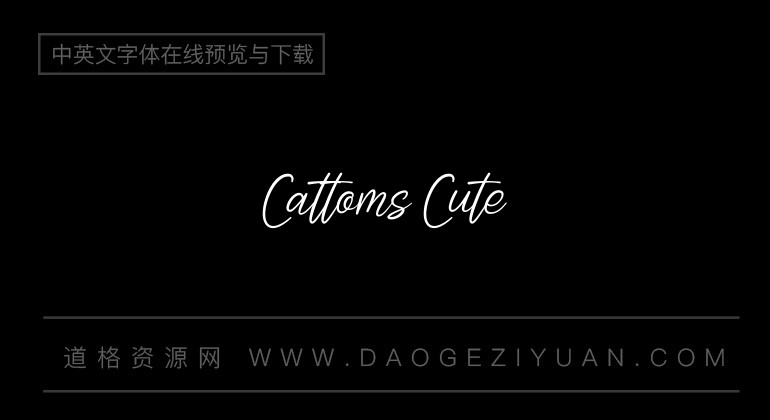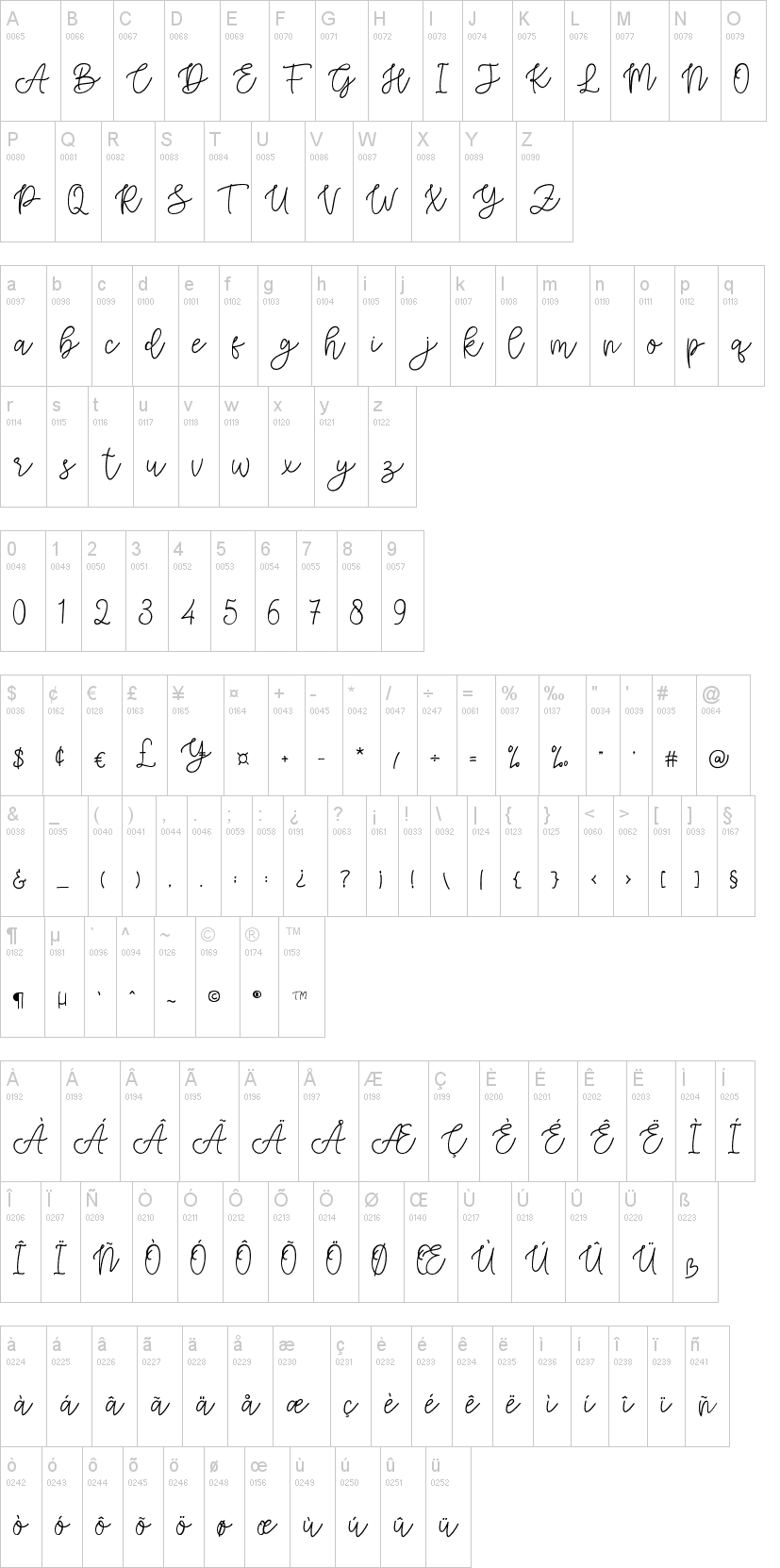
Cattoms Cute
Cattoms Cute 是一款卡通类的字体,它有着活泼可爱的样式,并且拥有大量的可爱的符号,可以用于排版,设计等等。Cattoms Cute 字体有着清晰的曲线和流畅的线条,可以为设计带来更多可能性,可以用于创作各种类型的文字,如漫画,插画,卡通,海报等等。
Cattoms Cute是一款非常不错的手写艺术字体,具有很好的视觉感,适合于文化类的宣传设计、商业类品牌的广告和产品包装设计以及个性化文字排版等较多场景。
Cattoms Cute字符映射图